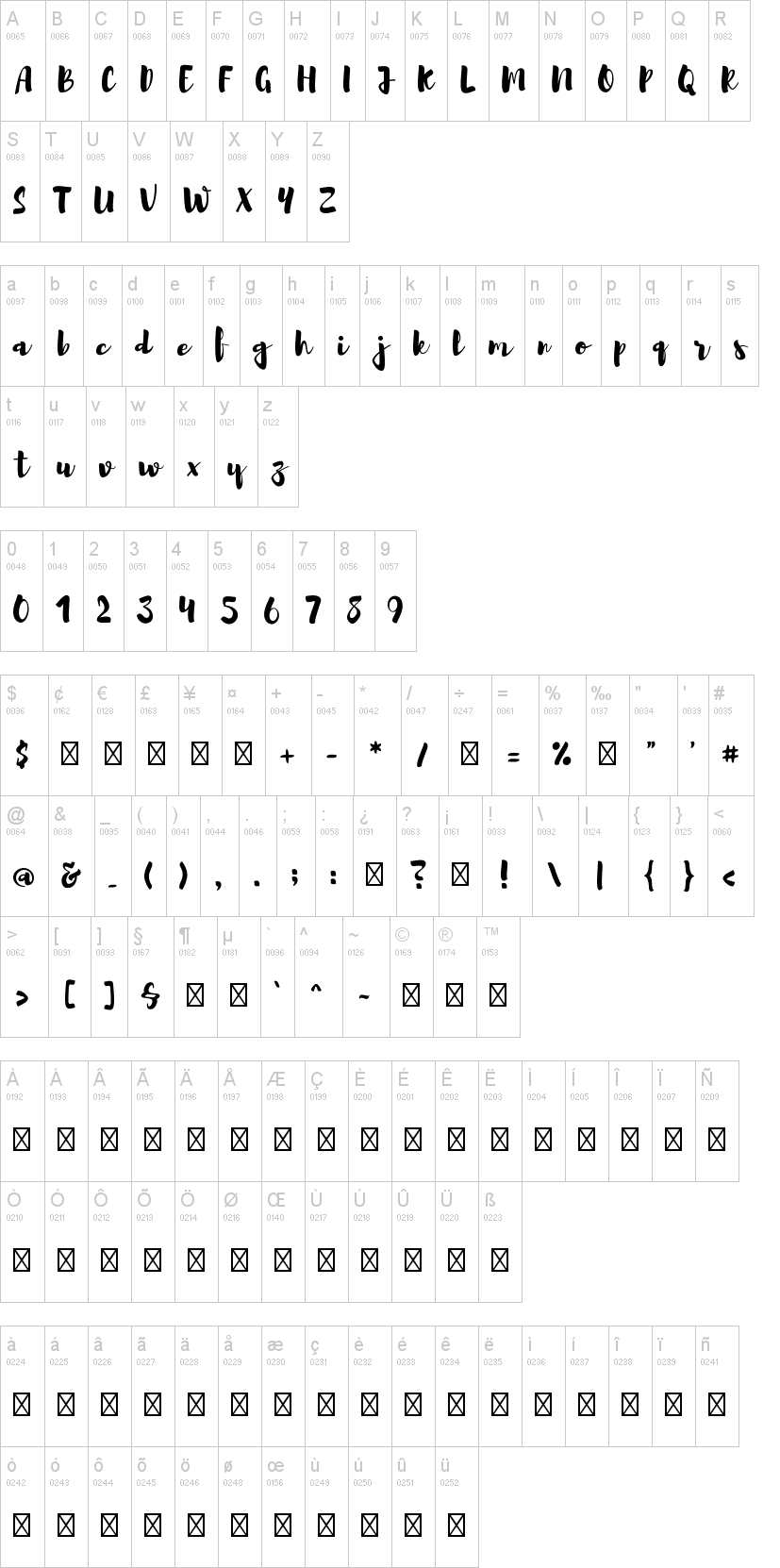
Brusher 字体是一款非常流行的手写字体,它具有自然、活泼的外观,能够很好地搭配各种设计风格。它的特点是斜体字形,具有较强的节奏感,能够让文字具有更多的表达力。此外,Brusher 字体还具有良好的可读性,可以让文字更加清晰可见,能够提升设计的质量。内容介绍
Brusher是一款非常不错的手写艺术字体,具有很好的视觉感,适合于文化类的宣传设计、商业类品牌的广告和产品包装设计以及个性化文字排版等较多场景。